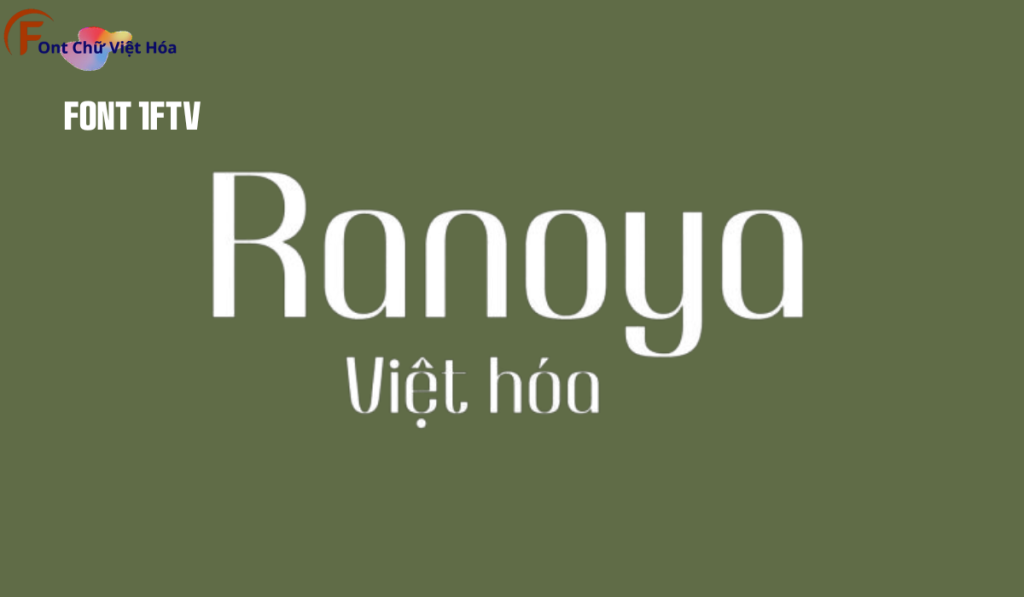
Font 1FTV Ranoya
Font 1FTV Ranoya là một font chữ độc đáo thuộc bộ 1FTV, mang phong cách sans-serif hiện đại với thiết kế mềm mại và thanh thoát. Được biết đến với các đường nét gọn gàng, không chân, 1FTV Ranoya tạo cảm giác tinh tế và chuyên nghiệp, phù hợp cho nhiều loại dự án thiết kế, từ website, branding đến các ấn phẩm in ấn. Font này đã được Việt hóa, giúp tối ưu hóa việc sử dụng trong các thiết kế dành cho thị trường Việt Nam. 1FTV Ranoya nổi bật với tính đa dụng và dễ đọc, làm cho nó trở thành lựa chọn lý tưởng cho cả văn bản chính lẫn tiêu đề.